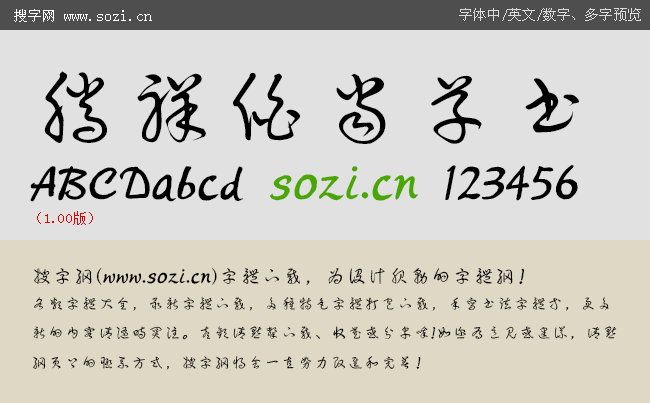
騰祥伯當(dāng)草書
搜字網(wǎng)給大家提供一款書法風(fēng)格的騰祥伯當(dāng)草書下載。由書法家王勇,字伯當(dāng)書寫完成。草書風(fēng)格鮮明、又具書法家的個(gè)性。草書意在結(jié)構(gòu)簡省、筆畫連綿。約定俗成的草法既具有法度的規(guī)范性,又具有很大的靈活性。草書的筆畫之間,字與字之間相互連帶呼應(yīng),作者書寫連貫流暢傳遞著一種奔放的情感。可用于印刷用字、顯示用字。